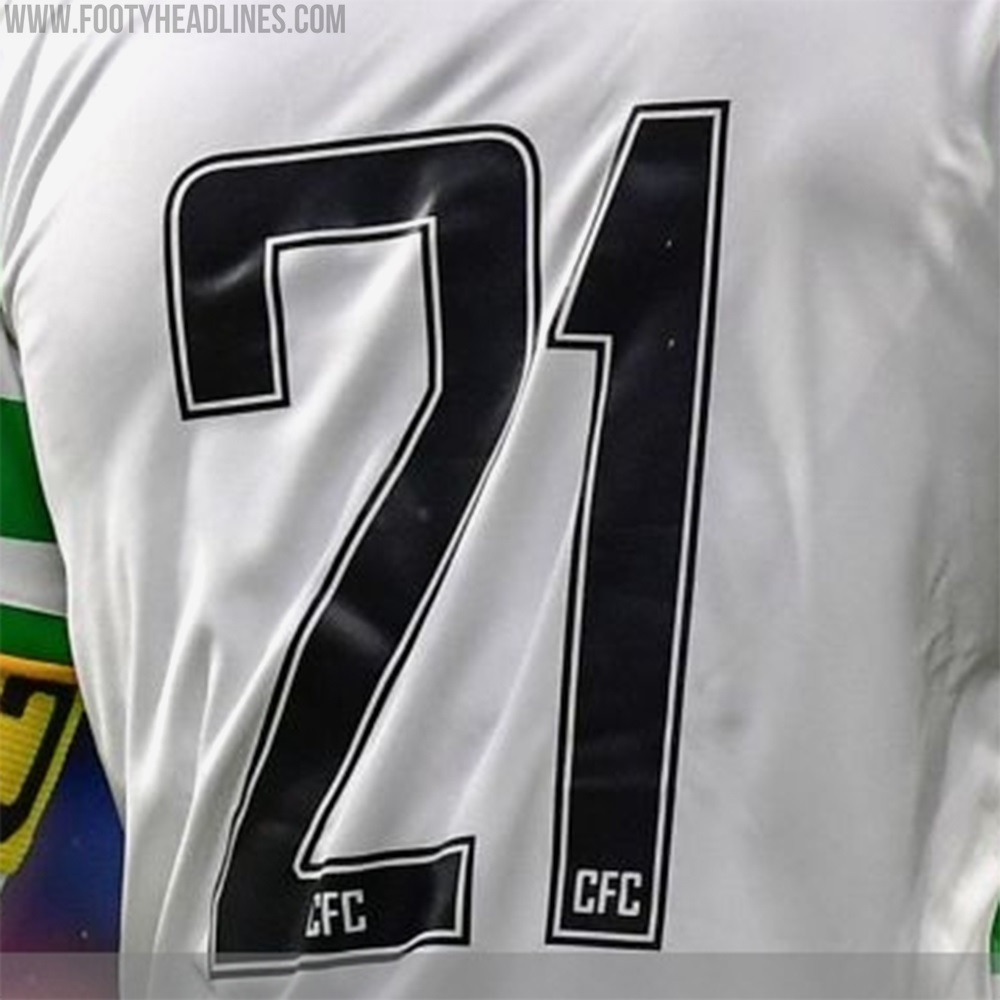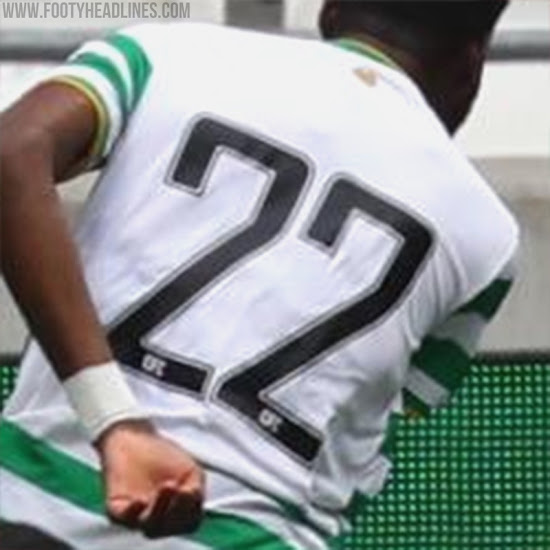
Celtic 20-21 Pokal-Trikotschriftart enthüllt - Zuvor verwendet von Lyon, Shakthar & anderen
Als Adidas Anfang Juli 2020 das neue Celtic Football Club 2020-21 Trikot auf den Markt brachte, gab es einige Kontroversen über die mögliche neue Celtic FC Trikot-Schriftart. Nun, da der schottische Klub einige Freundschaftsspiele ausgetragen hat und die schottische Premiership begonnen hat, werfen wir einen Blick auf die aktuelle Celtic FC Schrift...
Celtic 2020-2021 Pokal Trikot-Schriftart - Agency FB Schrift
Die Celtic 20-21 Trikot-Schriftart hat ein schmales, kantiges Erscheinungsbild, das auf den ersten Blick einzigartig aussieht. Die Celtic 20-21 Trikot-Schriftart ist jedoch keine Sonderanfertigung für den Verein, sondern basiert auf einer bekannten Schriftart.
Wie unser brasilianischer Follower Samarony Lima (@samaronylp) bemerkte, handelt es sich bei der Celtic 20-21 Trikot-Schrift eigentlich um eine offizielle Schriftart aus den 1990er Jahren - die Agency FB Schrift.
ATF Agency Gothic wurde 1932 von M.F. Benton als eine einzige Titelschrift entworfen. 1990 sah David Berlow Potenzial in den quadratischen Formen der schmalen, monotonen Buchstaben. Er entwarf einen Kleinbuchstaben und fügte einen Fettdruck hinzu, um Font Bureau Agency, einen sofortigen Publikumserfolg, zu erzielen. Da er weitere Möglichkeiten erkannte, arbeitete er mit Tobias Frere-Jones und Jonathan Corum zusammen, um Agency zu einer großen Serie zu erweitern, die fünf Gewichtungen in fünf Breiten für Text &Ampel; Display-Einstellungen bietet. Das Ergebnis ist die Agency FB Schriftart.
Scottish Premiership Die neue Celtic Adidas Trikot-Schriftart für Pokalwettbewerbe sieht ähnlich aus wie die offizielle Schriftart der schottischen Premiership
In der schottischen Premiership verwendet Celtic die ligaweite Schriftart. Die neue Celtic FC 20-21 Trikot-Schriftart scheint der offiziellen Schrift der schottischen Premiership ähnlich zu sein, insbesondere mit dem von Celtic gewählten Rahmenstil.
Am unteren Ende von Celtics Trikot-Schrift befindet sich das Akronym CFC im Agency FB Stil.
Celtic ist nicht die erste Mannschaft, die die Agency-FB-Schrift verwendet - der Schriftstil wurde bereits von Mannschaften wie Lyon, Shakhtar Donetsk und einigen brasilianischen Vereinen von Umbro verwendet.